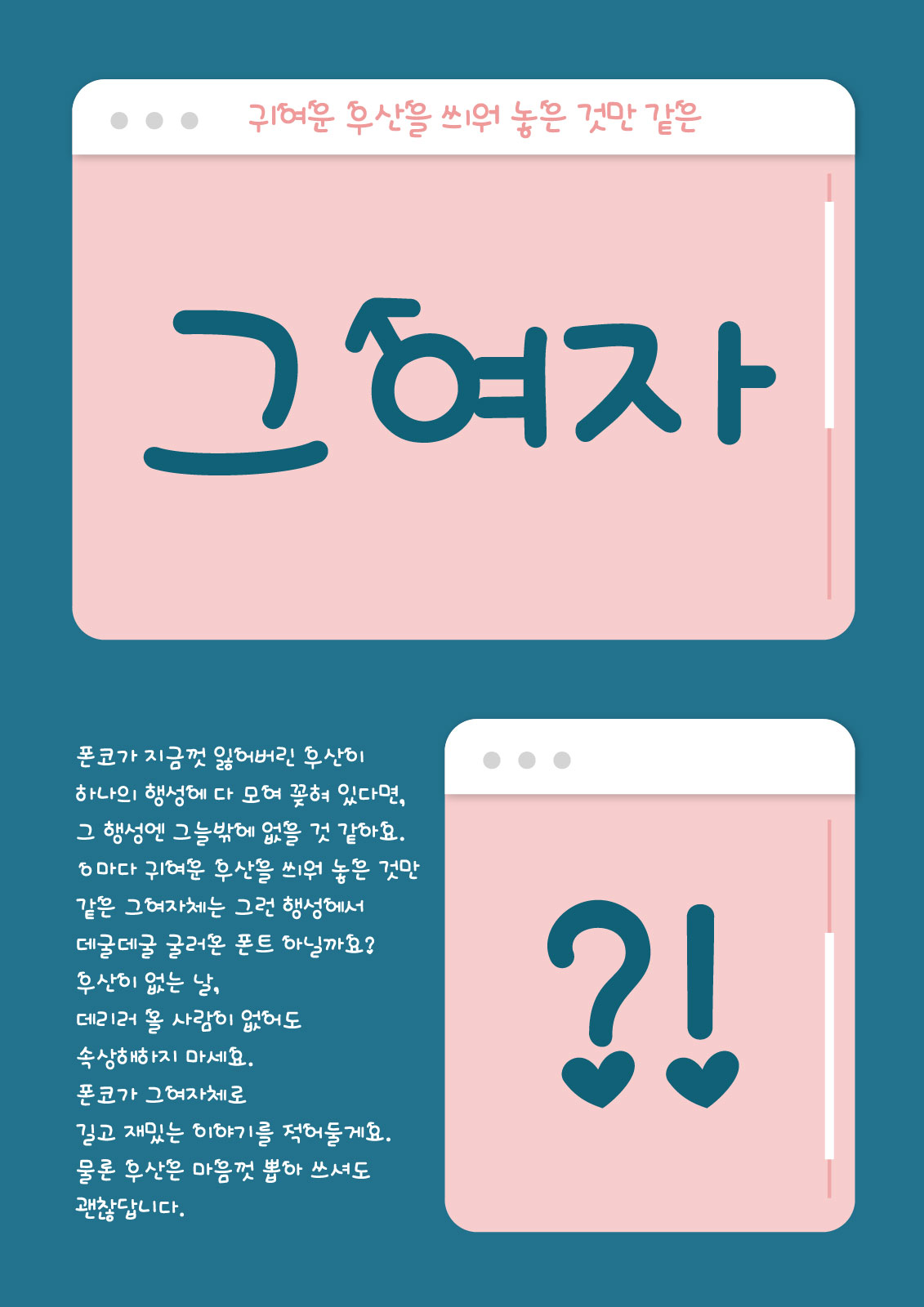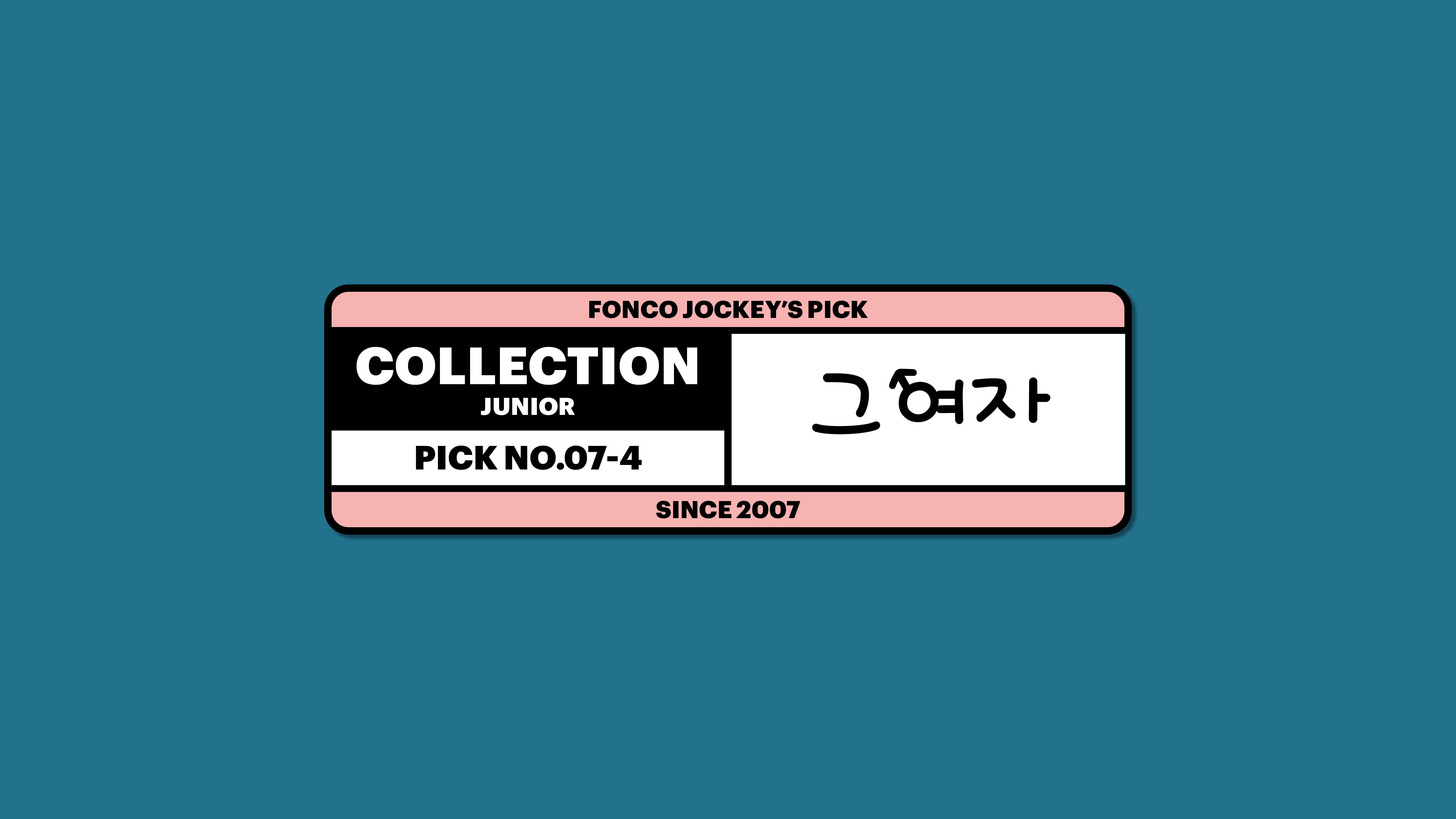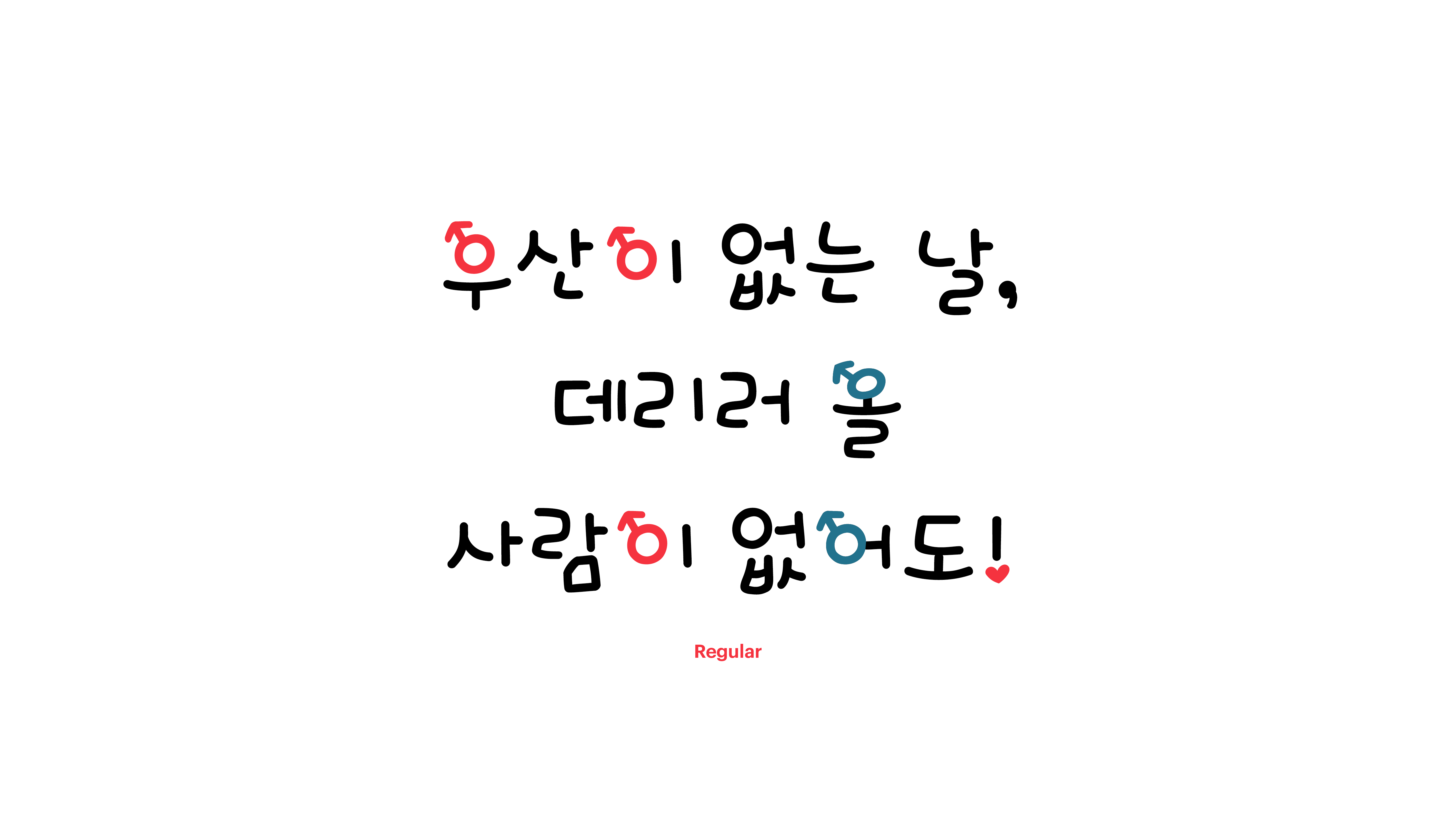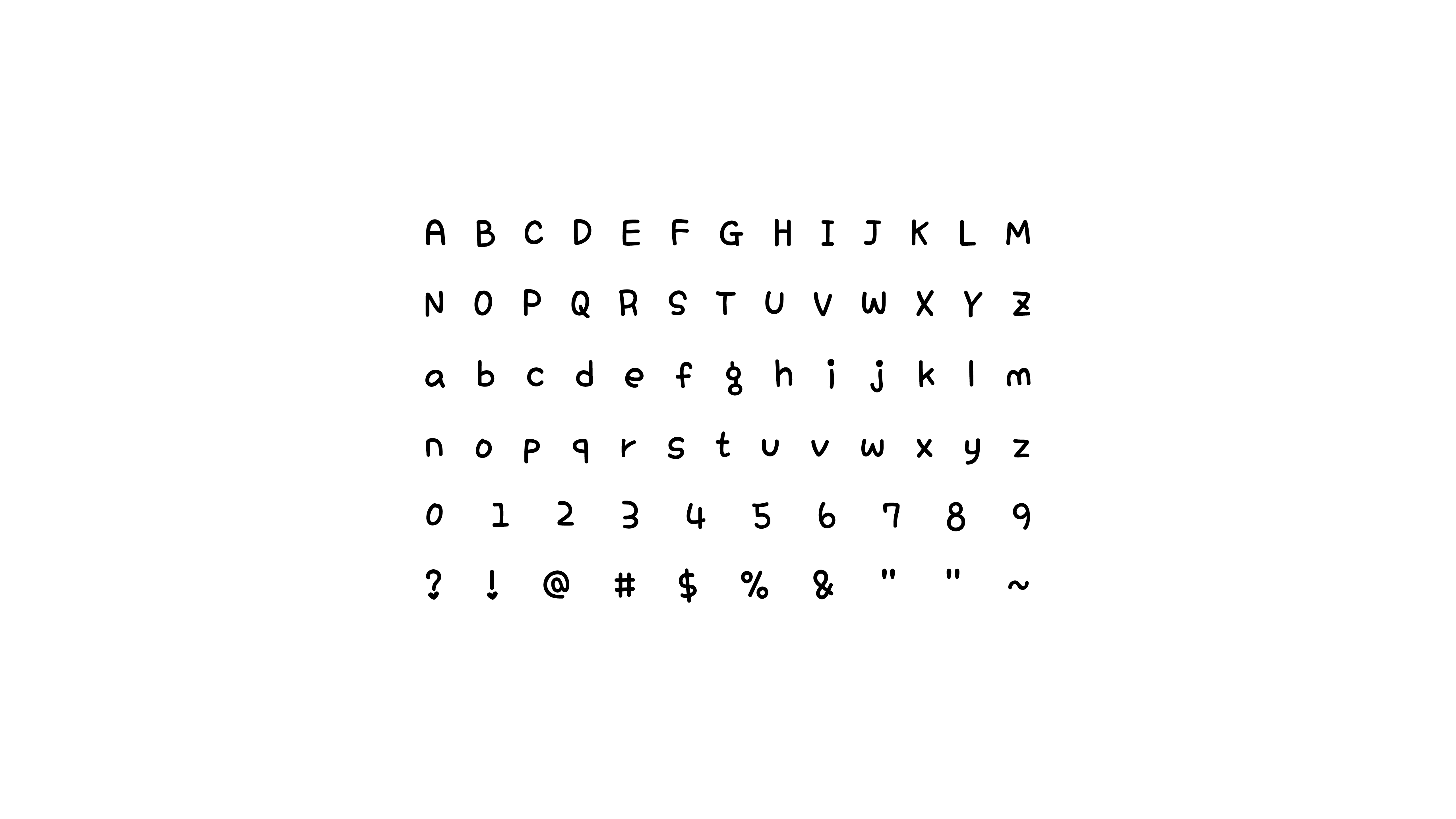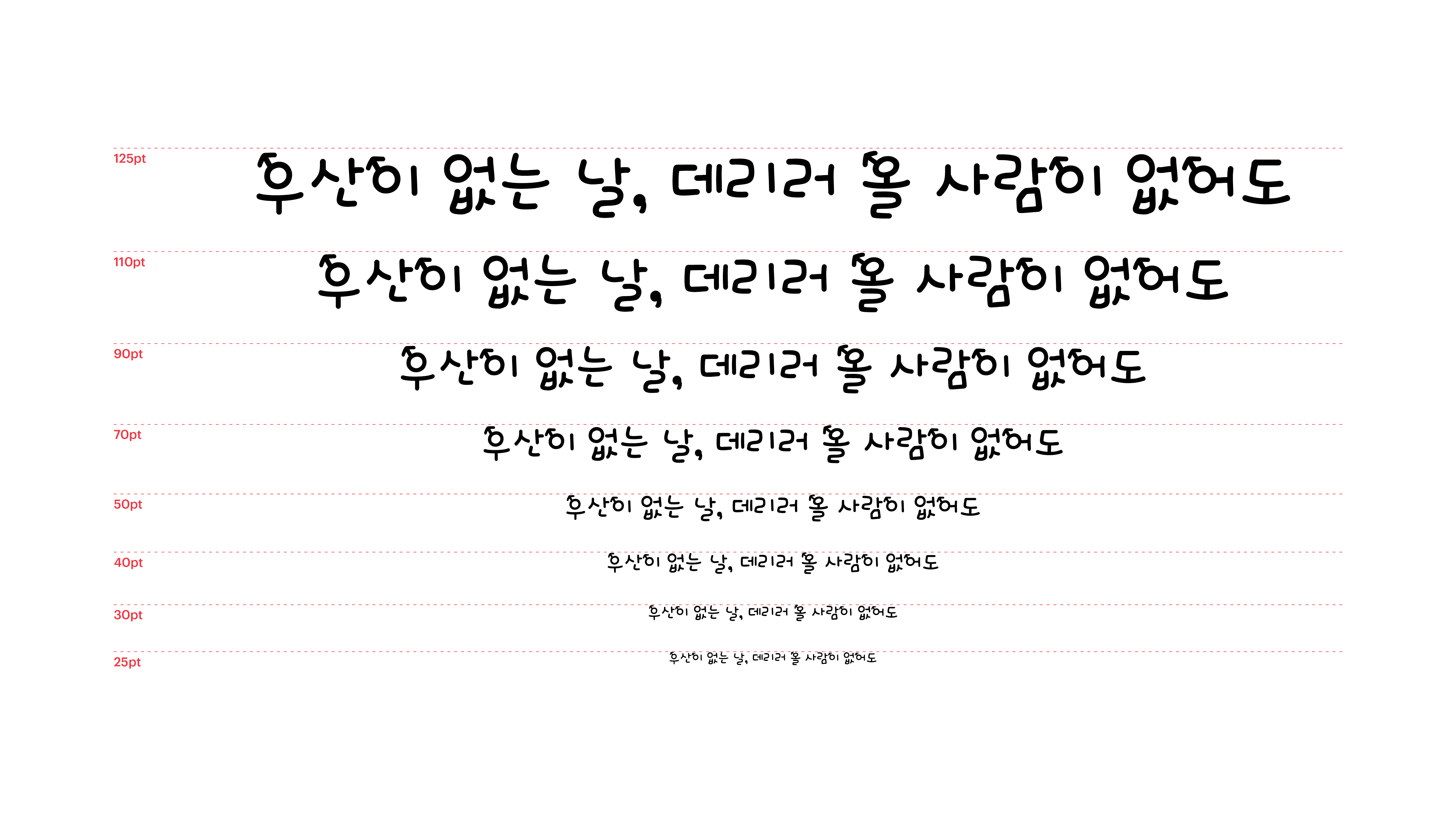
폰코가 지금껏 잃어버린 우산이 하나의 행성에 다 모여 꽂혀 있다면, 그 행성엔 그늘밖에 없을 것 같아요. ㅇ마다 귀여운 우산을 씌워 놓은 것만 같은 그여자체는 그런 행성에서 데굴데굴 굴러온 폰트 아닐까요? 우산이 없는 날, 데리러 올 사람이 없어도 속상해하지 마세요. 폰코가 그여자체로 길고 재밌는 이야기를 적어둘게요. 물론 우산은 마음껏 뽑아 쓰셔도 괜찮답니다.
Yoon 그여자